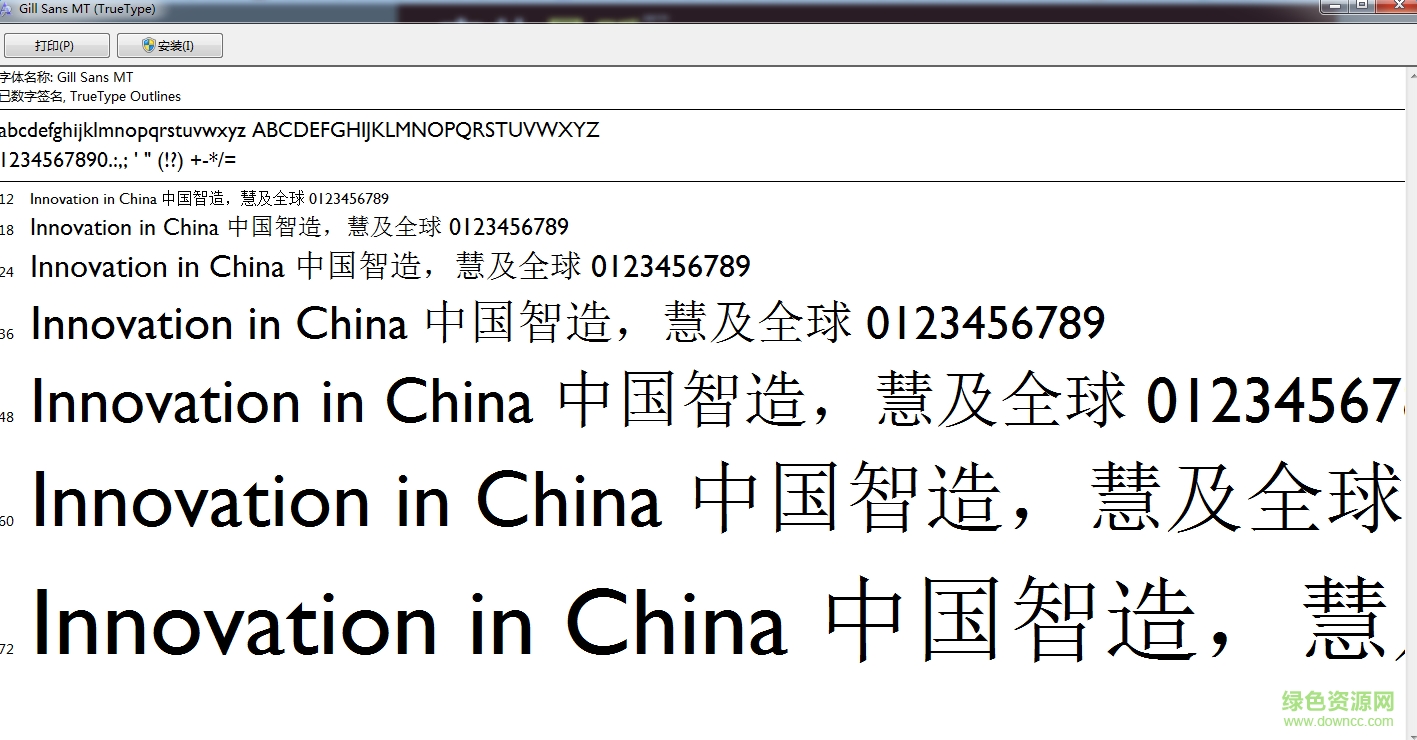
gill sans mt字體是一款可讀性極高的英文字體,字型飽滿,字體線條流暢,看上去明快大方,實(shí)用性強(qiáng),打印效果也非常出色,歡迎大家在綠色資源網(wǎng)下載!
Gill Sans字體是Monotype公司1928年設(shè)計(jì)的一種字體,Gill Sans字體被指定為第28屆雅典奧運(yùn)會官方打印字體,大概這種字體的設(shè)計(jì)師吉爾先生(Eric Gill)也預(yù)想不到,無論潮流如何變化,技術(shù)如何發(fā)展,他設(shè)計(jì)的字體會顯示出如此強(qiáng)大的生命力,而且Gill Sans字體還與奧運(yùn)會的要求非常吻合。